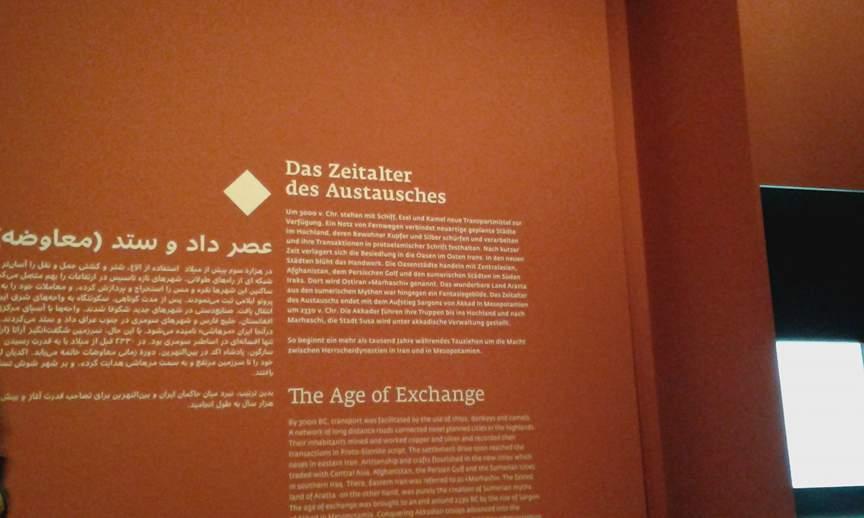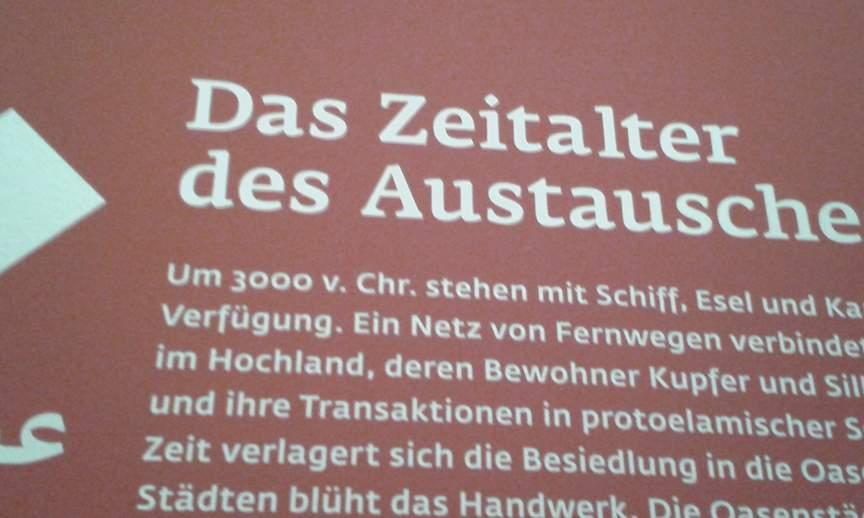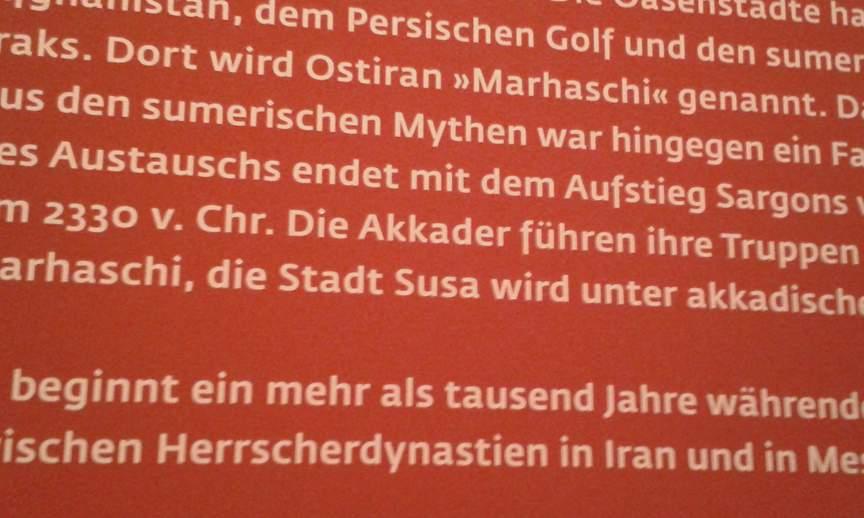
Schriften in der Bundeskunsthalle
ich war vor ein paar Tagen in der Iran-Ausstellung der Bundeskunsthalle in Bonn. Mir haben die dortigen Schriften ganz gut gefallen, kann mir jemand sagen, worum es sich da handelt? Leider hab ich keine besseren Fotos … Das erste zeigt eine Th-Ligatur und verschiedene Schriftstärken, die anderen beiden etwas mehr Details.
Jo, das sieht sehr danach aus (f mit Unterlänge, karo-förmige i-Punkte, passender arabischer Font). Vielen Dank!